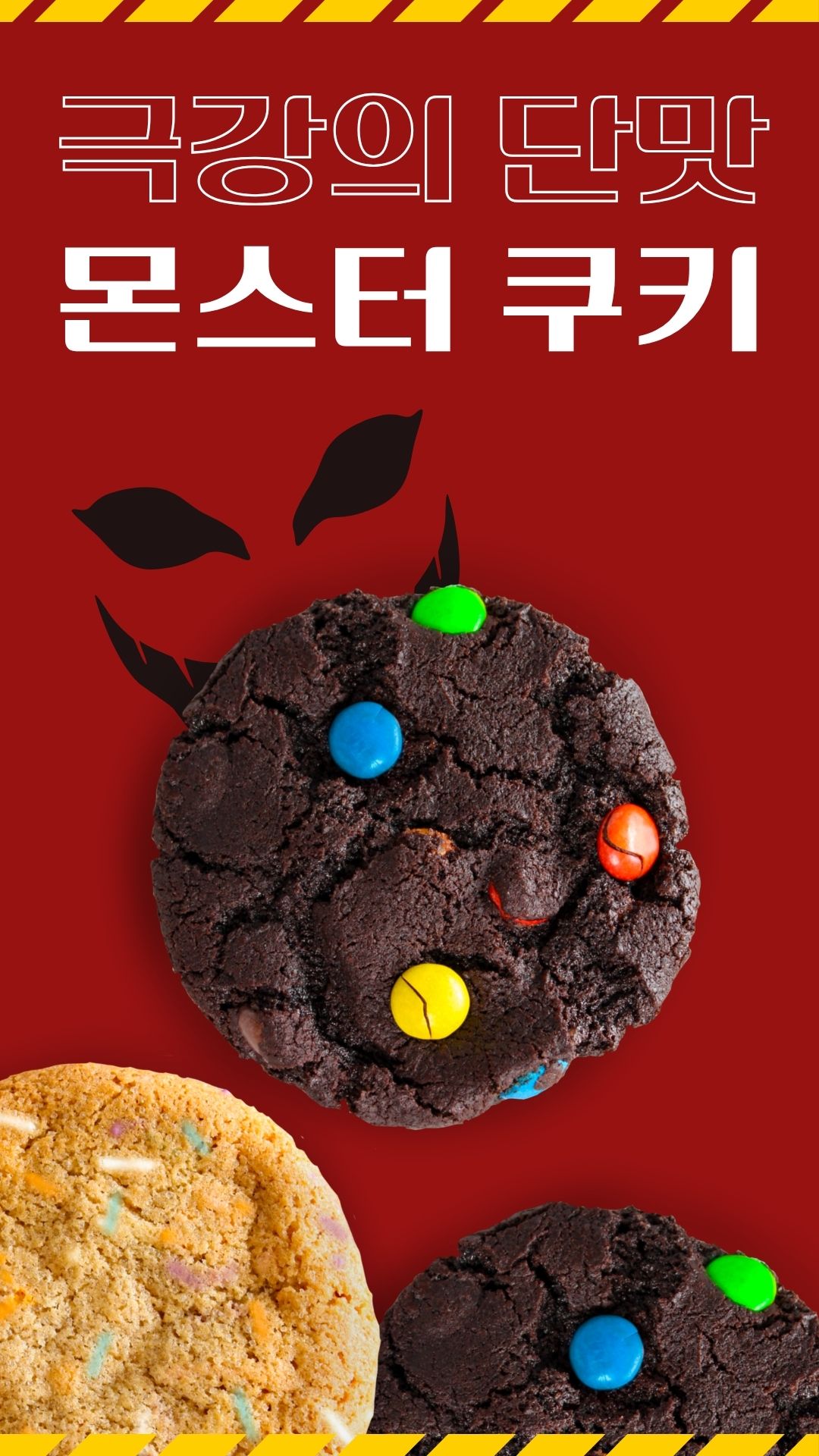
하남다움체 무료폰트
하남다움체 — 하남시에서 배포하는 무료 폰트입니다. 세로획 모서리만 굴려 단단하고 부드러운 고딕체
하남시가 2023년에 공개한 전용서체로, 폰트릭스가 만들었습니다.
이름의 뜻을 제작사가 풀어 두었습니다. 인간다움처럼 앞에 붙는 단어를 그만의 특징으로 명명하는 방식에서 착안했다는 것입니다. 그러니 하남다움은 하남 그 자체의 정체성이라는 뜻입니다. **서체 이름은 시민 공모와 투표로 정해졌습니다.**
만든 방식이 특이합니다. 새로 그린 것이 아니라 **기존 하남시 로고타입의 특징을 반영해 발전시키는 방식**으로 제작했습니다. 조형 설명도 구체적입니다. 굵은 세로획과 얇은 가로획의 시원한 획 대비로 역동적으로 표현했고, 좌측 상하단의 일정한 굴림은 기존 로고타입의 가장 큰 특징을 반영한 것이며, ㅅ 계열 자소의 여유로운 곡선과 꽉 찬 네모꼴의 단단함이 특징이라는 것입니다.
구성이 특이합니다. 굵기가 아니라 **제목용과 본문용 두 벌**로 나뉩니다. 현대 한글 11,172자를 모두 담아 어떤 글자를 넣어도 빠지지 않습니다. 공공누리 제1유형이라 상업적으로 쓸 수 있지만 **출처 표시가 의무**입니다.